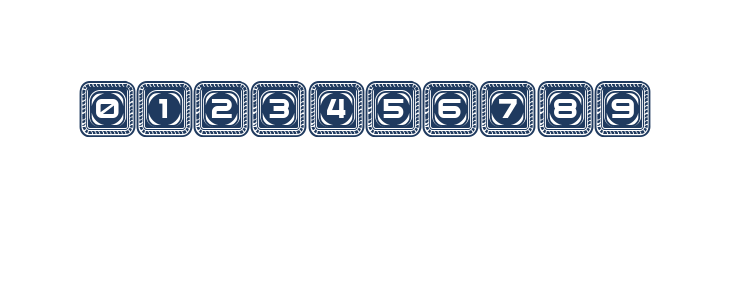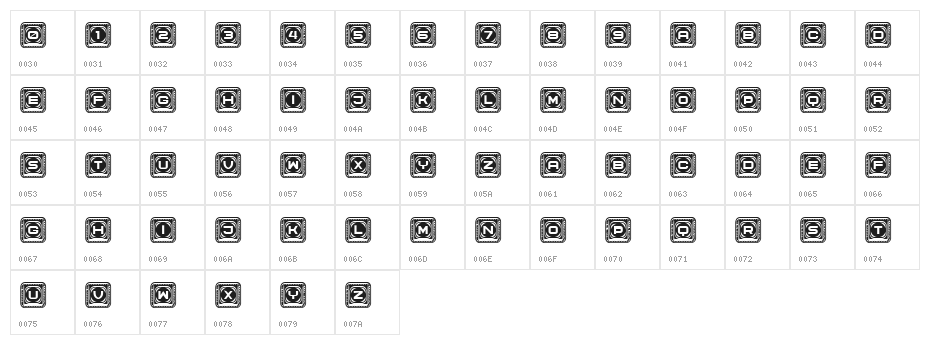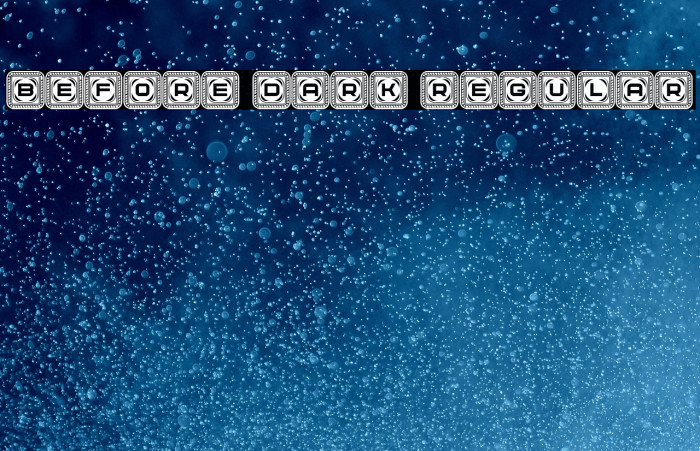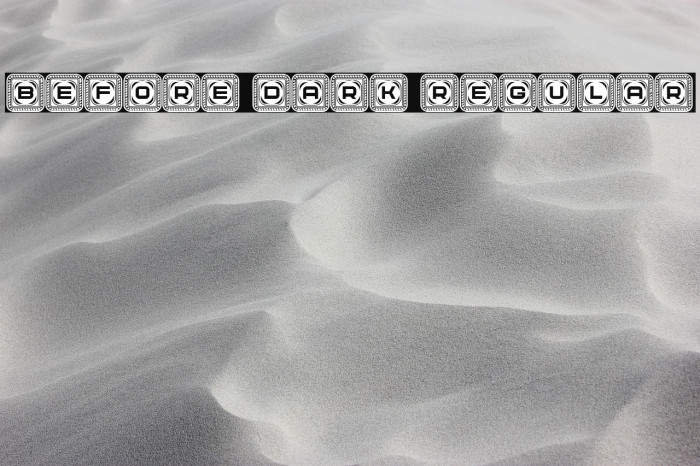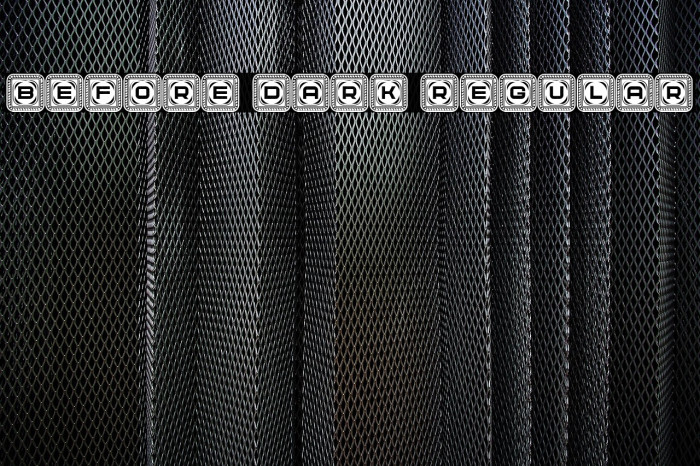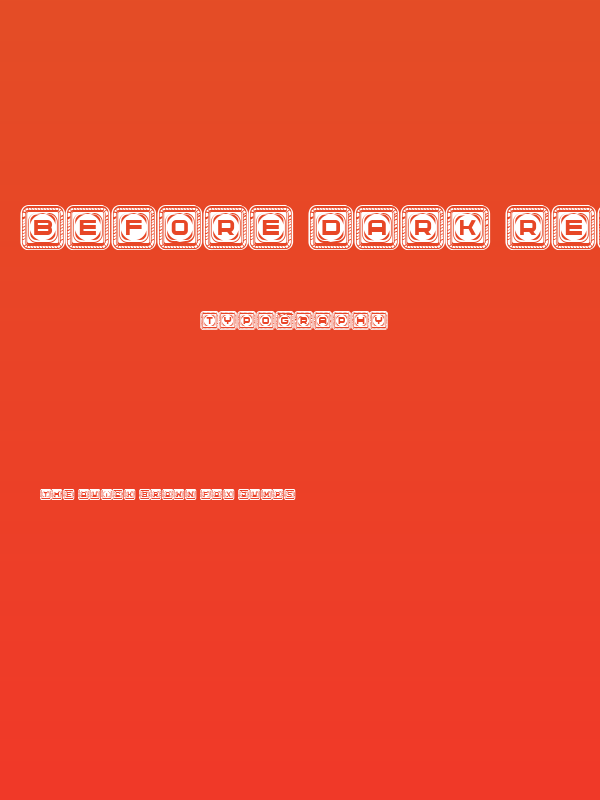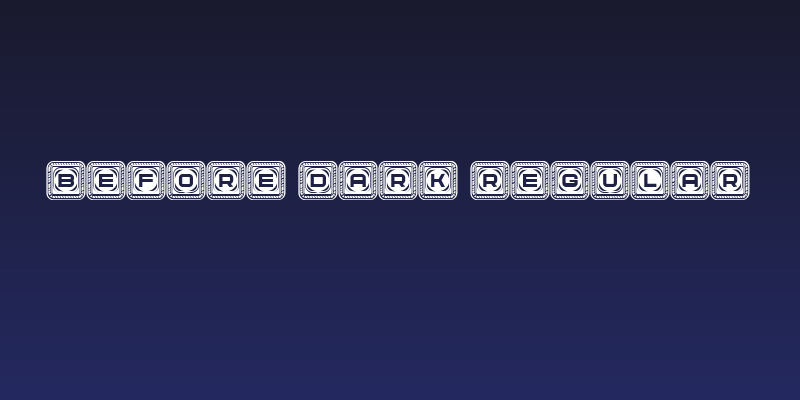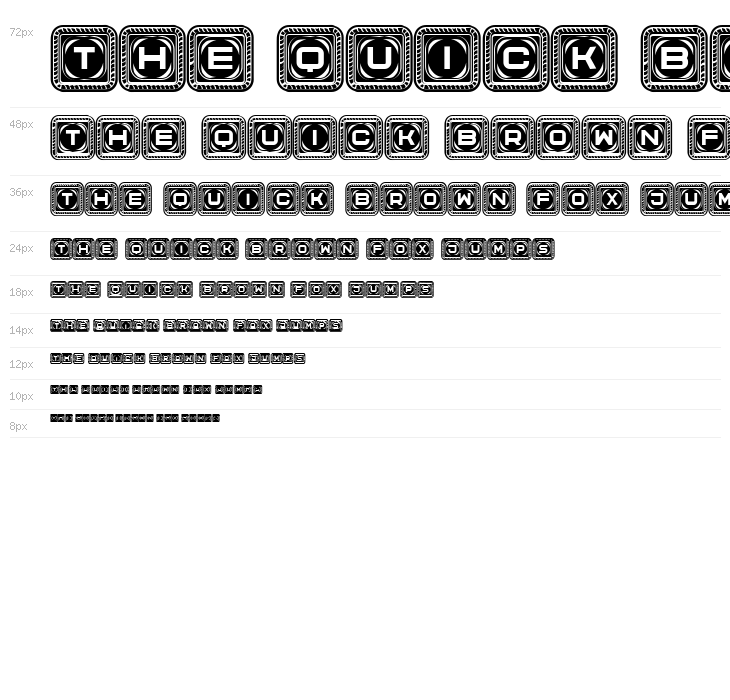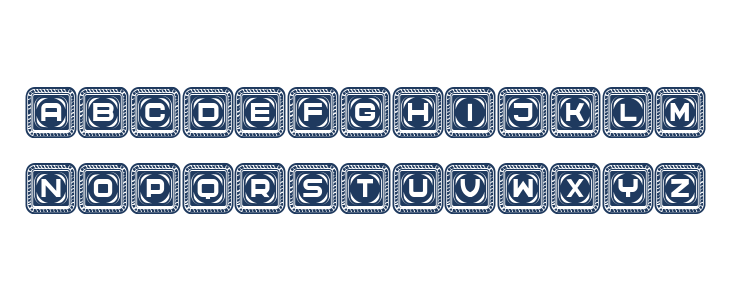
Before Dark Regular Font
| Progetti proposti | Ideal for vintage-themed posters, retro branding, signage, and creative design projects that require a standout, nostalgic look. |